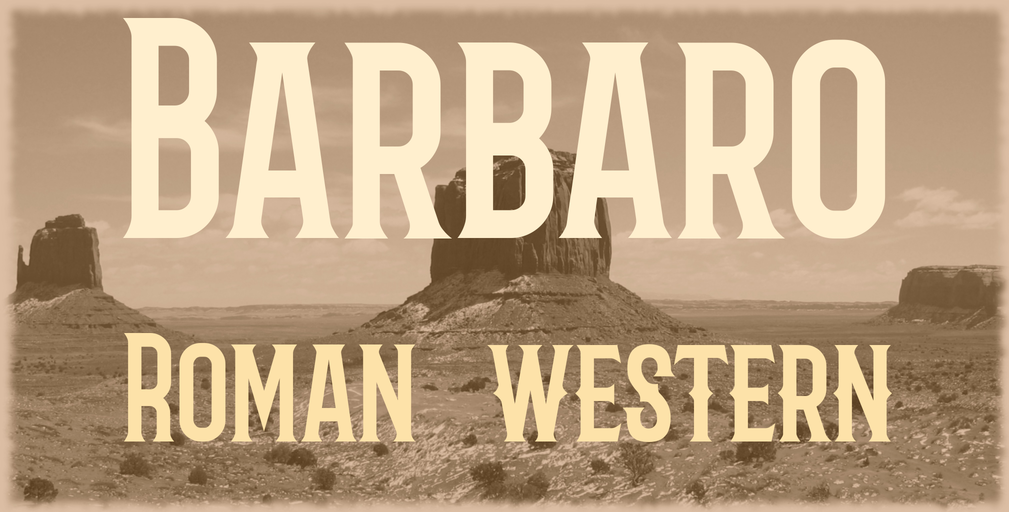
A Barbaro Font Family é uma família de tipografia para uso em desafios visuais que requerem destaque e impacto visual. Seu designer, Hamilton, criou esta fonte para atender à necessidade de textos mais dramáticos e interativos. As letras dessa família são marcantes, com traços largos e arredondamentos bem definidos, o que as torna ideais para marcas de título ou qualquer outro uso onde deseja destacar seu conteúdo. A Barbaro está disponível nas duas categorias mais populares – Serif e Sans-serif. Em termos de categoria Display Fonts, a Barbora é uma escolha ótima para criar texturas arrojadas em sites, cartazes ou publicações digitais. Suas linhas grossas contrastam com os detalhes sutis do design de cada letra, criando um contraste visual interessante. A Barbaro também oferece grandes opções de personalização graças à sua ampla gama de estilos e variantes. Com a Barbaro Font Family na sua coleção, você pode dar uma nova dimensão às suas criações digitais, seja em sites, impressões ou redes sociais. Este é mais que apenas uma fonte: ele representa um estilo de atitude visual, pronto para fazer o seu trabalho de impactar e atrair a atenção do público visando seus objetivos específicos.